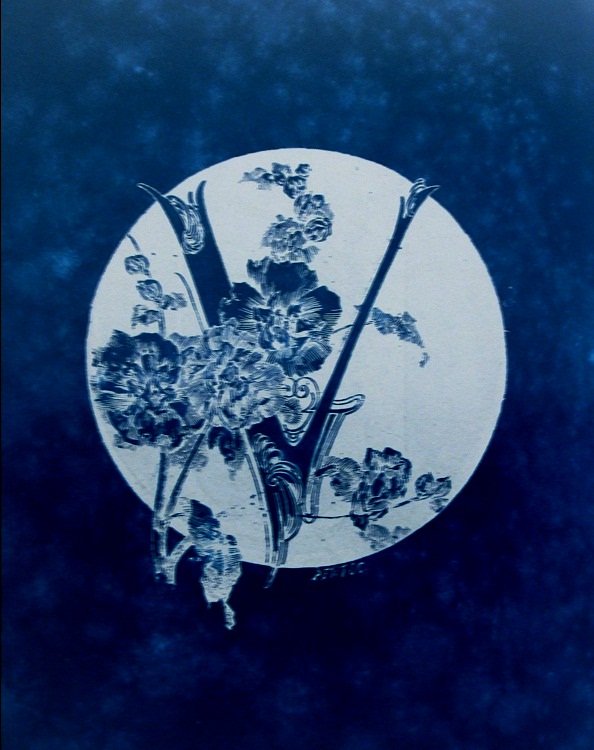
| Carácter Japonés |
Hace poco se ha inaugurado una exposición muy interesante en el "CaixaForum" de Barcelona titulada "JAPONISME La Fascinació per l'art Japonès"
Unas de las figuras más importantes en la ilustración de libros en el periodo del modernismo en Cataluña fueron entre otros: Apel.les Mestres y Alexandre de Riquer (Clicar para ver excelentes artículos en Vikipedia). La influencia del estilo Japonés es introducida por la estética Prerafaelista en la que ellos desarrolaron parte de sus obras. A estos dos artistas debemos el diseño y la ilustración de títulos como "Liliana" y "Gaziel" de A. Mestres y "Crisantemes" y "Anyorances" de A. de Riquer, títulos marcados por una estética claramente oriental.
| Diseño del cartel para promoción del libro "Anyoranses, 1902. |
| "Anyorances", M. de Riquer, 1902 |
En el diseño de letras también encontramos algunas muestras de abecedarios con clara influencia oriental en diseñadores de esta época, veamos primero el bonito alfabeto de Habert Dys, circa de 1890, (Clicar para ver entrada completa) basado en motivos de la naturaleza pero con una clara estética japonista:
| N-W / W-N |
| O |
| E |
| F-E / E-F |
| Caracteres Japoneses |
Dentro de la producción del diseñador y tipógrafo Lewis Foreman Day.(Clicar para mas información) Encontramos también dos alfabetos al estilo oriental:
| Alfabeto al estilo Japonés |
| Alfabeto al estilo Chino en esquinas cuadradas |
Y finalmente he separado un alfabeto entero al estilo japonés de la serie de MUSTER ALPHABETE, verschiedener Schriftarten In den Neuesten Formen nº 7
La caligrafía japonesa y china no solo han influenciado solo en el periodo del modernismo, en el trazó gestual y la composición han influenciado en el proceso de abstracción que ha sufrido la caligrafía en el
s. XX , como ejemplo podemos ver la obra del famoso calígrafo francés: Claude Mediavilla y en especial sus preciosos cuadros abstractos, (como no también recomendar el célebre libro: "CALIGRAFÍA: DEL SIGNO CALIGRÁFICO A LA PINTURA ABSTRACTA" Valencia, 2005, Campgràfic.)